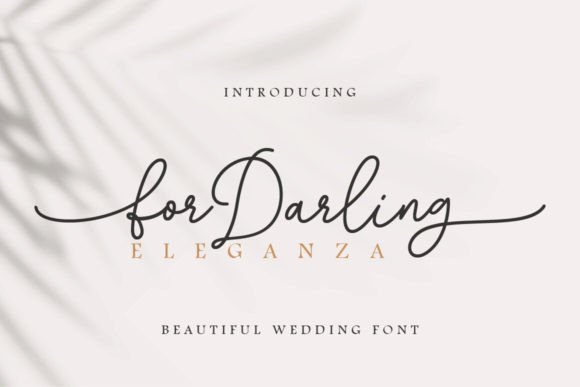
For Darling
如果您正在寻找像 For Darling 这样的高质量素材,这个高级套餐是您创意项目的绝佳选择。
精心制作的 For Darling 提供干净的矢量、流畅的排版以及让您安心的商业许可证。
无论您是创建 POD(按需打印)产品、婚礼邀请函还是社交媒体图形,For Darling 都是理想的选择。